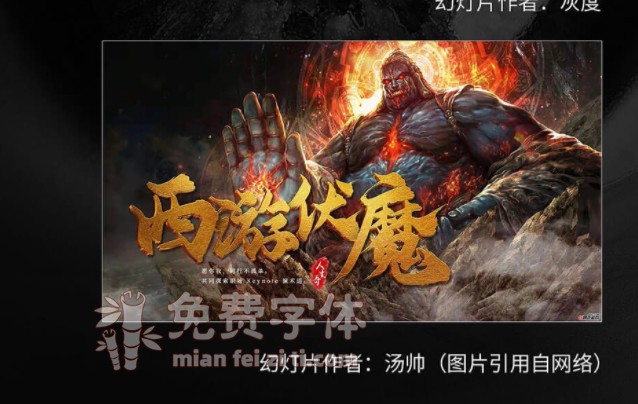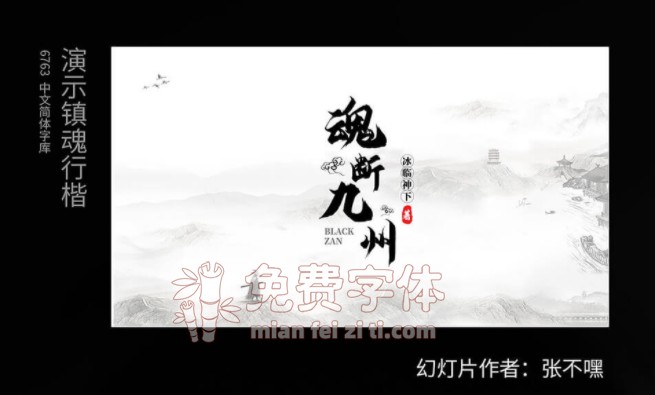
演示镇魂行楷:披着收费的皮却拥有免费商用之心字体(9.9元)字体资讯
这套演示镇魂行楷的作者是Keynote研究所的人生哥,说起keynonte研究所,他们迄今为止已经发布了三套免费商用字体供大家使用了,分别是演示悠然小楷、 演示佛系体、演示斜黑体,他们发布的每一套字体,无论是免费商用还是非免费商用,都是精品,可以看得出他们对字体的认真与执着。 还有一个可能大家还不知道的事情,就是另外一款免费商用的鸿雷板书简体也是因为受Keynote研究所的人生哥的影响而诞生的。
对于人生哥来说,真的不觉得他能通过这款字体能赚得了什么钱,做这一套字体所花费的精力与时间,是大家所想像不到的。为了这一套字体,他还推掉了全部幻灯片定制,还有字由和字魂的字体收购要约,只是为了让大家能使用到更便宜的商用字体!